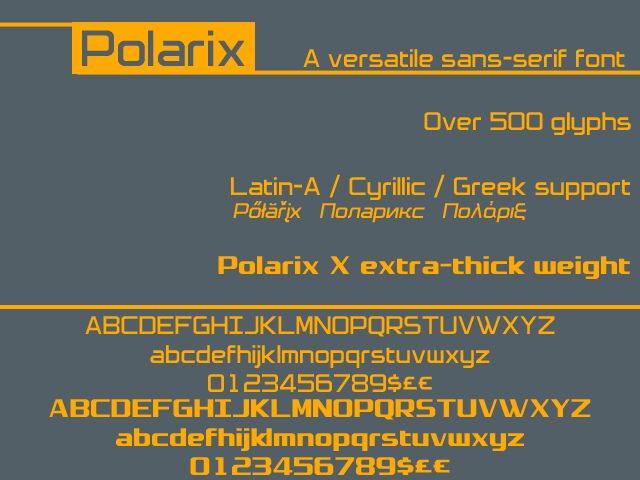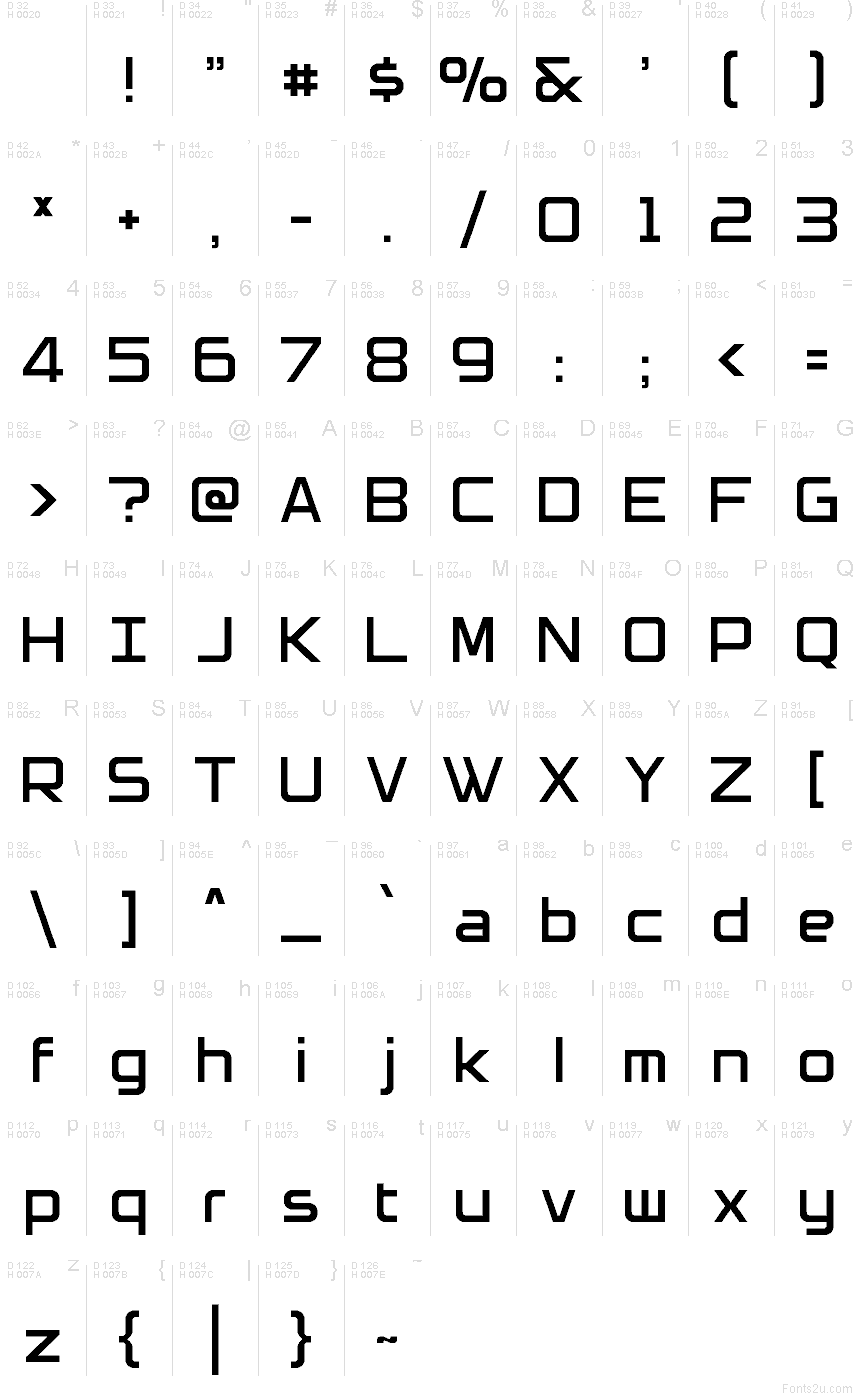
Polarix هو خط هندسي مجاني للعناوين من تصميم أليكس ريتشاردز، يستخدم أشكالاً مستطيلة مستديرة وقطعاً حاداً ليمنح الحروف مظهراً مدمجاً ووحدوياً. بفضل منحنياته العريضة وجوانبه المسطحة، يبدو الخط وكأنه ألواح مصممة بدقة بدلاً من كونه خطاً عادياً بلا زوائد (Sans Serif)، مما يضفي على التصميم إيقاعاً حاداً وعصرياً.
تعتبر هذه الكتلة المتماسكة مثالية للعلامات التجارية التقنية، ورسومات الألعاب، وعناوين التطبيقات، والملصقات، والتغليف، حيث تتطلب الكلمات القصيرة حضوراً بصرياً قوياً. كما يمكن استخدامه كقاعدة للشعارات والعناوين الرئيسية، خاصة عندما تبحث عن مظهر أنيق وتقني دون الانزلاق إلى المظهر التقليدي لأفلام الخيال العلمي.
تم إنشاء وإطلاق Polarix و Polarix X في عام 2022 عبر منصة FontStruct.
Designer description: <p>A really versatile futuristic sans-serif. Contains a whole bunch of language support.</p>